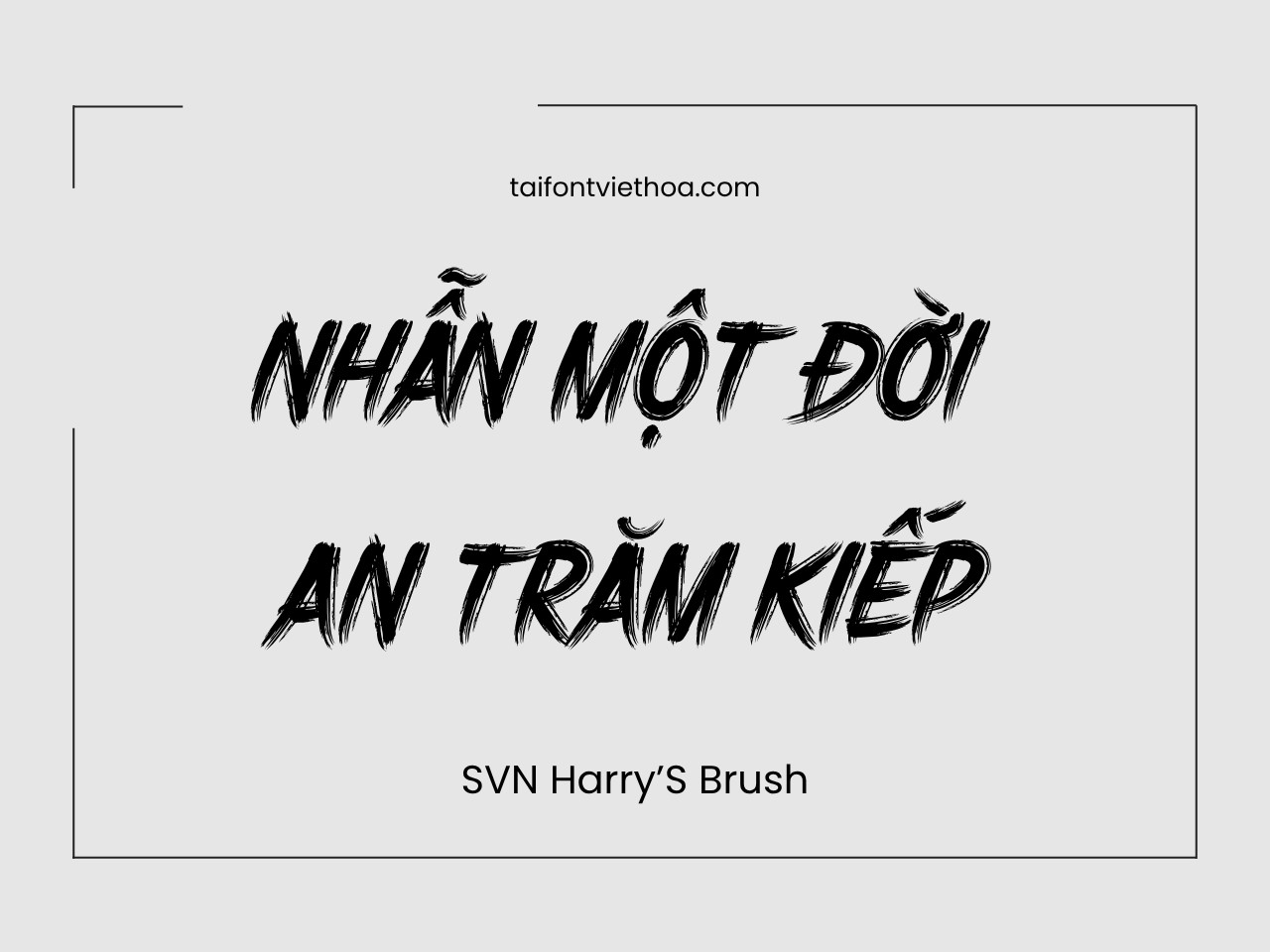
Giới thiệu về font SVN Harry’S Brush – Kiểu chữ brush viết tay năng động, cá tính và sáng tạo
SVN Harry’S Brush là phiên bản Việt hóa của font Harry’S Brush – một kiểu chữ brush mang phong cách viết tay đầy năng lượng, cá tính và sáng tạo. Font được thiết kế với các nét cọ dày, mềm mại và uyển chuyển, tạo nên cảm giác tự nhiên và gần gũi, rất phù hợp cho các dự án thiết kế poster, quảng cáo, thiệp mời và truyền thông mạng xã hội.
Phiên bản Việt hóa của SVN Harry’S Brush đã được Taifontviethoa.com chỉnh sửa kỹ lưỡng, hỗ trợ đầy đủ dấu tiếng Việt cùng hơn 60 ngôn ngữ khác. Font giúp các nhà thiết kế dễ dàng ứng dụng trong nhiều dự án sáng tạo mà vẫn giữ được phong cách trẻ trung, cá tính và độc đáo.
Thiết kế brush mạnh mẽ – Lý tưởng cho thiết kế sáng tạo và truyền thông trẻ
SVN Harry’S Brush sở hữu các nét chữ dày, mềm mại với hiệu ứng cọ chân thực, tạo cảm giác năng động và biểu cảm. Font phù hợp sử dụng cho tiêu đề, poster, bài đăng mạng xã hội hoặc các sản phẩm sáng tạo cần sự nổi bật và cá tính. Phong cách thiết kế của Harry’S Brush rất thích hợp với các dự án quảng cáo, truyền thông, thời trang và nghệ thuật.
Ứng dụng lý tưởng: thiết kế poster quảng cáo, bài đăng mạng xã hội, thiệp mời, bao bì sản phẩm, logo thương hiệu trẻ trung và các dự án sáng tạo cần phong cách độc đáo, cá tính. Ngành nghề phù hợp: truyền thông, quảng cáo, thời trang, giải trí, nghệ thuật và các thương hiệu định vị theo phong cách trẻ trung, sáng tạo.